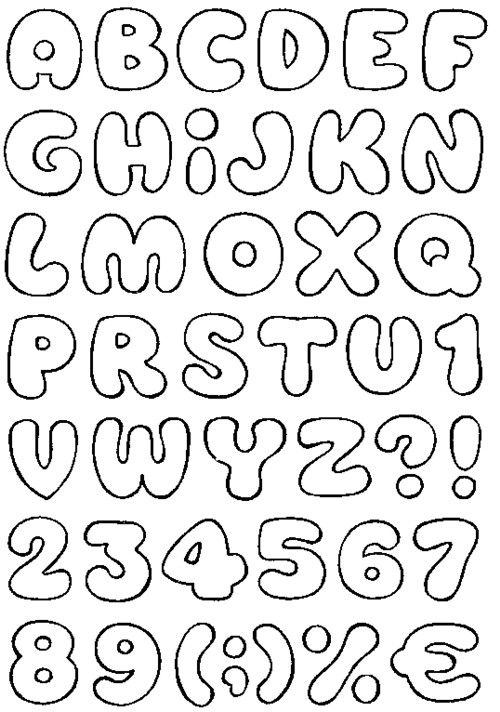
«Ты помнишь, как всё начиналось?…» Часть 7 и последняя. Шрифты
Ну, и в завершение воспоминаний о первых моих оформительских опытах не могу не упомянуть о шрифтах.
Здесь всё просто — буковки используются в поздравительных надписях и всяких подобных вещах и оформляются исключительно по желанию автора.
№ 1 — шрифт «Намёк»
Для его использования необходимо сначала нарисовать «дорожку» нужной ширины и длины (это может быть ровный прямоугольник или нечто извилистое, вроде ленты).
Далее эту «дорожку» нужно поделить на примерно равные по ширине квадратики (в случае ленточно-извилистого оформления получатся не квадратики, а трапеции).
В квадратики начинаете быстро вписывать задуманный текст и наслаждаетесь простотой процесса (недаром же «намек» называется).
№ 2 — «колобковый шрифт»
Эти симпатичные буквы сейчас, кажется, не использует только ленивый — очень уж они распространены.
Можно использовать с обводкой или без обводки.
А еще — можно взять за образец и придумать что-то свое.
№ 3 — «оформительский шрифт»
Как правило, в нем весь задуманный текст пишется одним цветом, но что мешает попробовать пофантазировать?
№ 4 — «древнерусский шрифт»
О, этот шрифт имеет для меня свою историю.
На самом деле, его использование относится к несколько более поздним временам, когда в 10 классе меня по признаку хороших оценок записали в специализированный педагогический класс.
Профилирующие предметы (кому что было нужно для подготовки в ВУЗ) там вели преподаватели местного педагогического университета, что было большим плюсом.
Но был и большой минус — поскольку класс был именно педагогический, нас натаскивали в том числе и по педагогике и заставляли «учиться работать с детьми».
После 10 класса всех обязали проходить т.н. «практику» в виде отработки целой лагерной смены в качестве вожатых (без всякого намека хоть на какую-то оплату).
Со мной возникла проблема — я в учителя идти категорически не собиралась (уже тогда была настроена на поступление на юрфак), свои права как будущего медалиста знала и с детьми за бесплатно возиться отказывалась.
После долгих переговоров я отработала-таки эту смену… в качестве художника-оформителя 🙂
Вот где пригодились все эти известные мне приемчики и окончательно укоренившаяся к тому времени в организме склонность к креативу.
Целыми днями я сидела в одном кабинете с начальницей лагеря и творила — стенгазеты, объявления, задники для сценок, наброски грима. Еще писала статьи о лагерных мероприятиях в духе «ой ты, гой-еси, добры молодцы», для чего пришлось найти в домашней библиотеке (спасибо запасливому папе, в годы дефицита волокшему в дом практически любую книгу, какая ему попадалась!) и проштудировать в поисках нужного стиля сборник древнерусских басен. А еще — пришлось разработать на основе той же книги этот самый древнерусский шрифт, ведь при такой тематике смены, как «богатыри, красны-девицы, история, культура», без него было просто не обойтись.